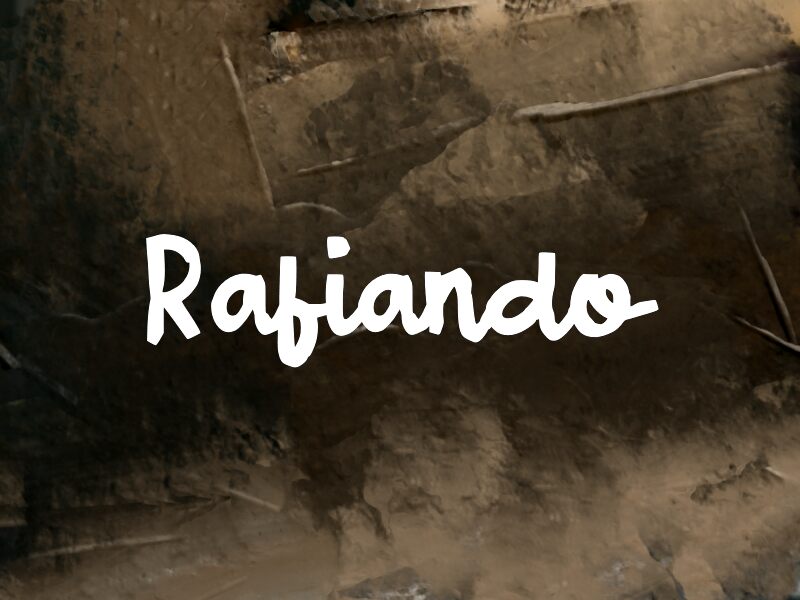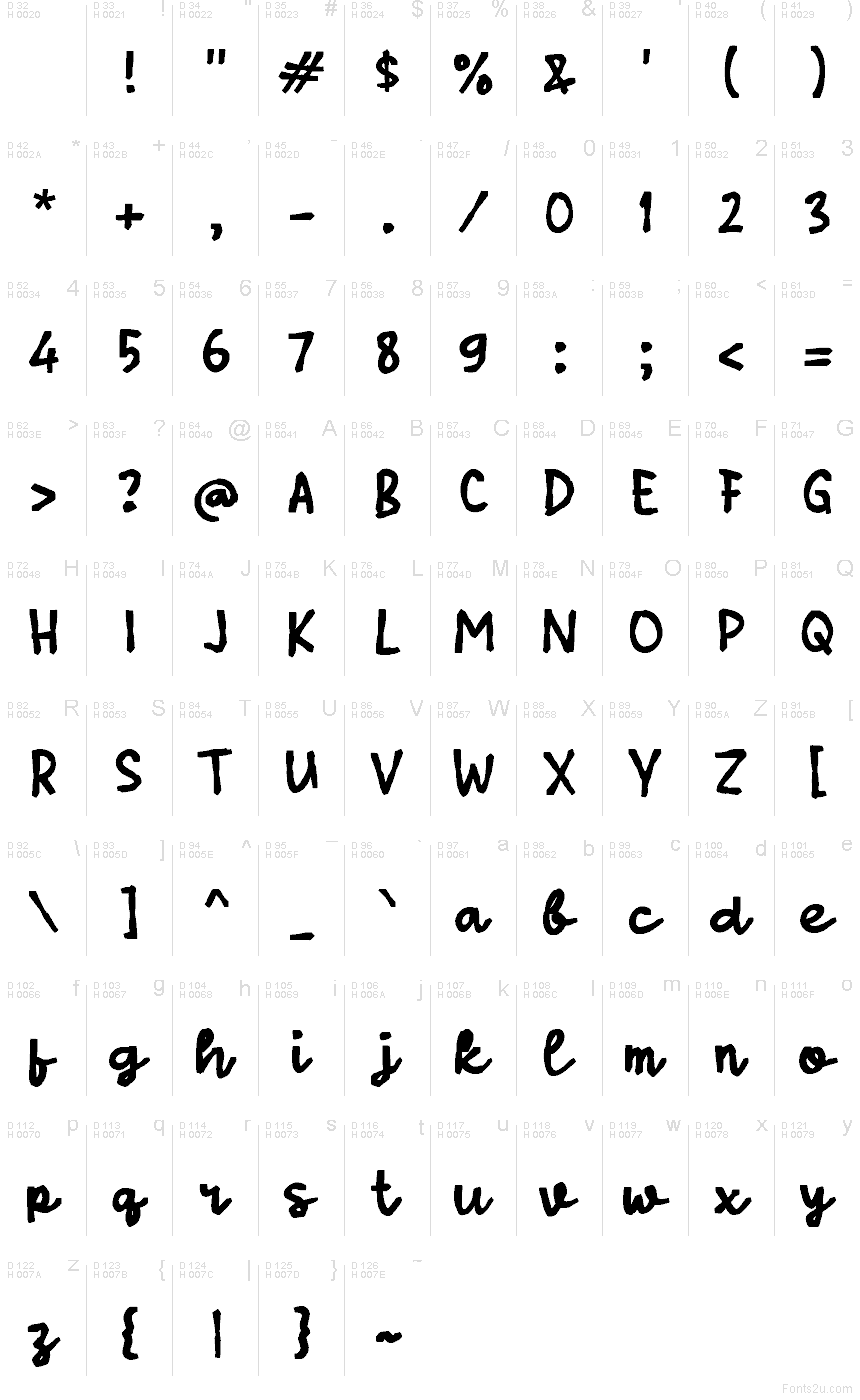
Rafiando от Wep — это бесплатный рукописный шрифт в стиле brush script с эффектом рисования от руки. Буквы выглядят широкими и насыщенными, с округлыми формами, неровными краями штрихов и легкой небрежностью, которая делает надпись живой и естественной.
Он идеально подходит для брендинга кафе, упаковки снеков, заголовков постеров, графики для соцсетей и оформления обложек, где нужен теплый и «крафтовый» эффект. Как бесплатный шрифт, Rafiando лучше всего проявляет себя в коротких фразах, логотипах и названиях, ведь его густые кистевые штрихи и непринужденный ритм придают даже простым словам дружелюбное настроение.
Rafiando
Презентация и наглядный образец шрифта Rafiando